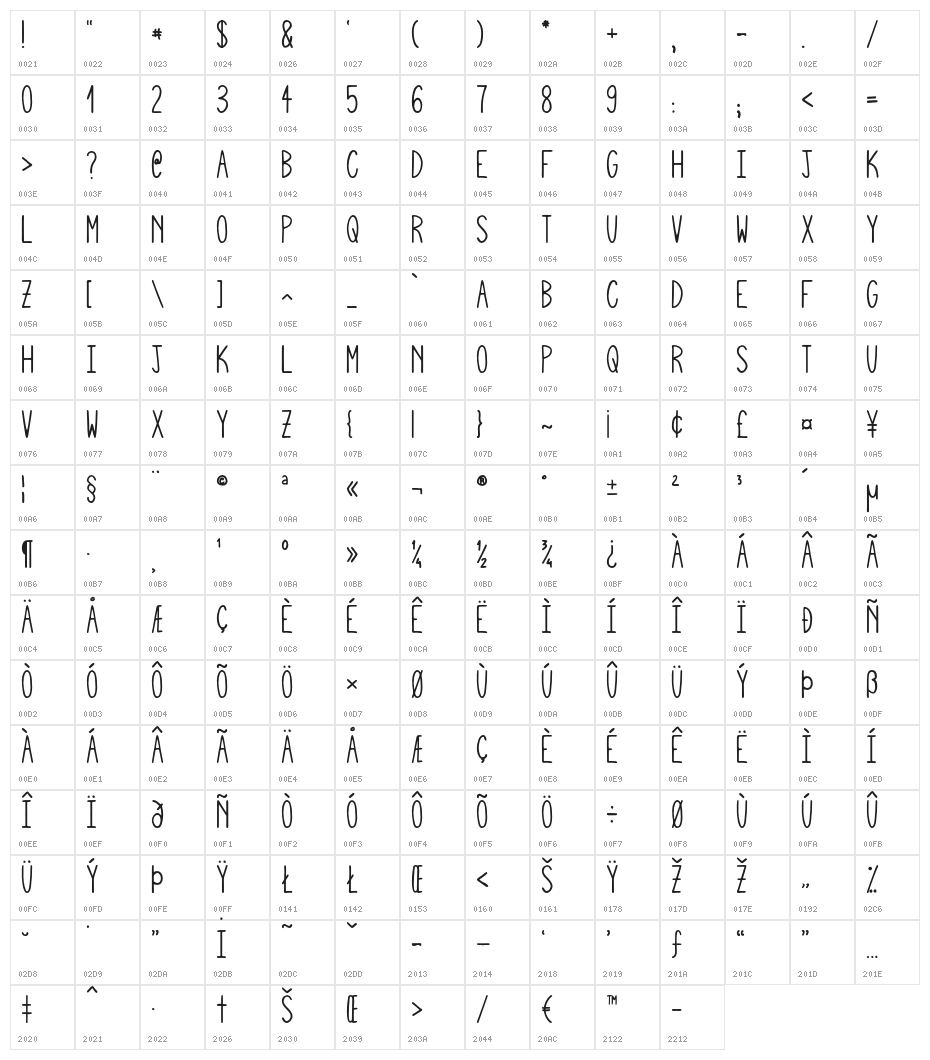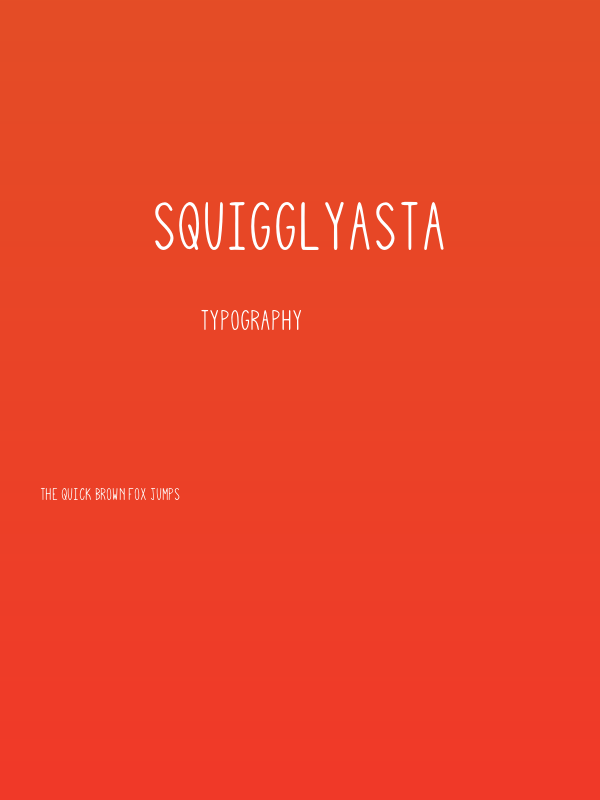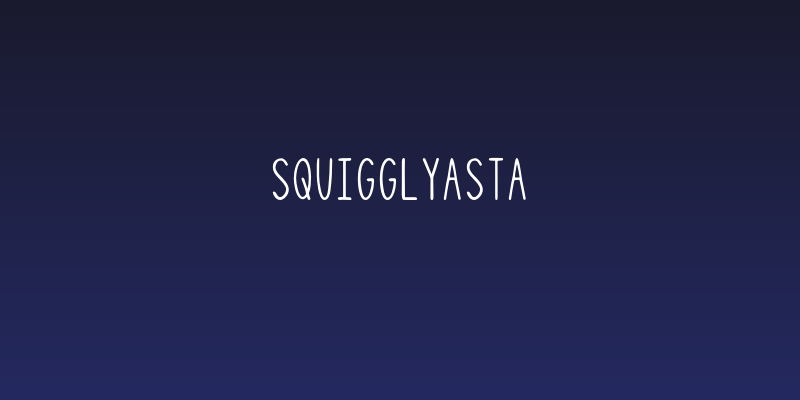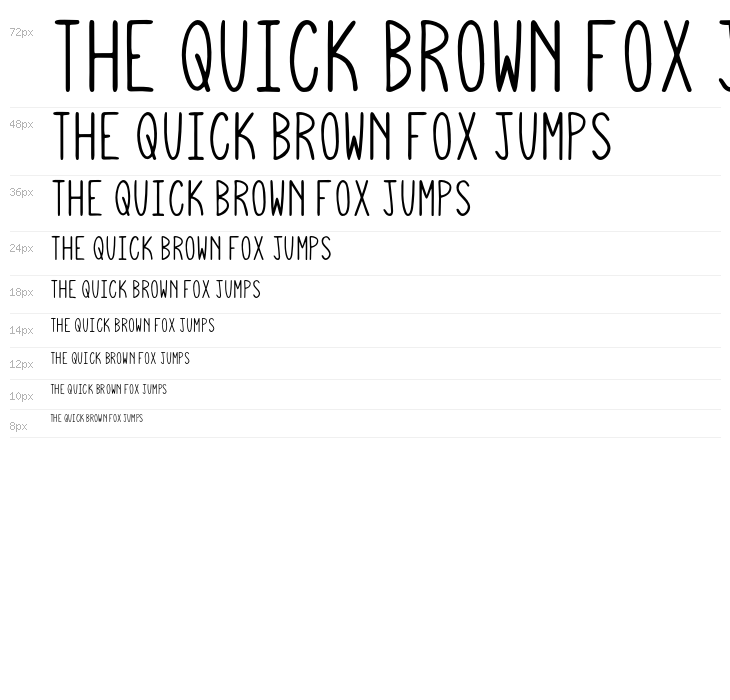
SquigglyAsta Font
| Caso d'uso | Headlines, Logos, Informal Text |
| Progetti proposti | Ideal for children's books, greeting cards, playful branding, and informal invitations. |